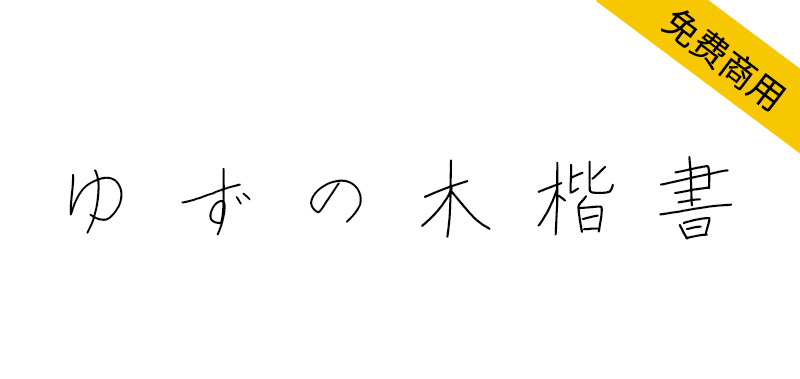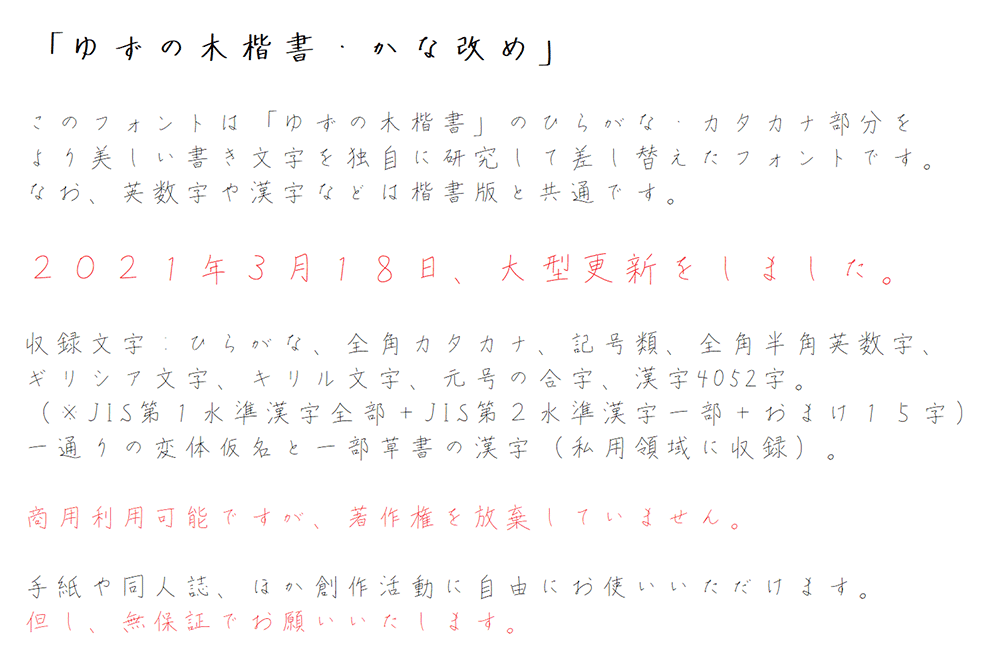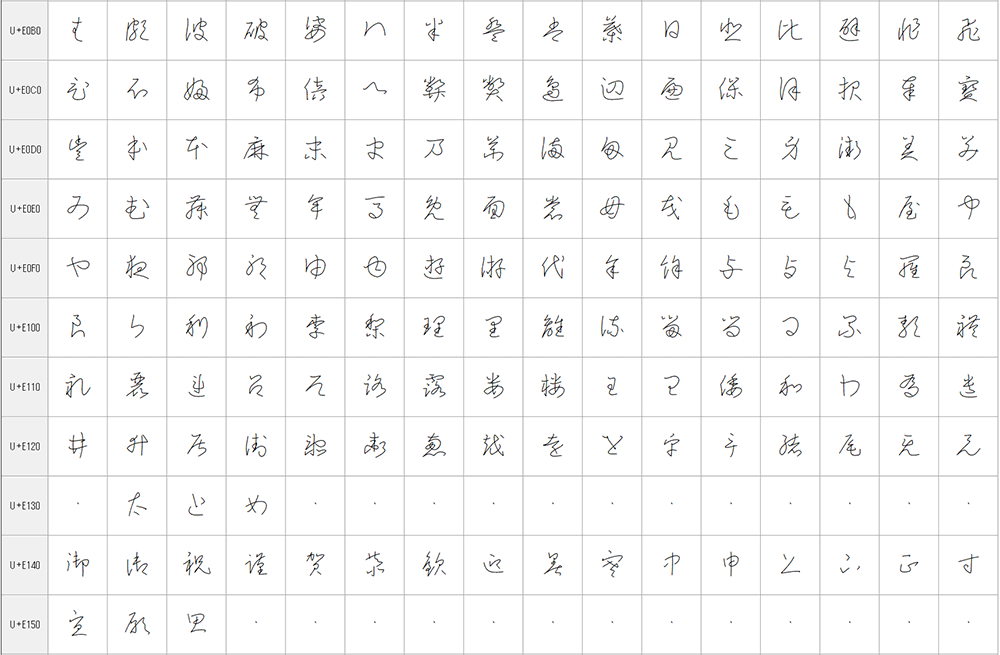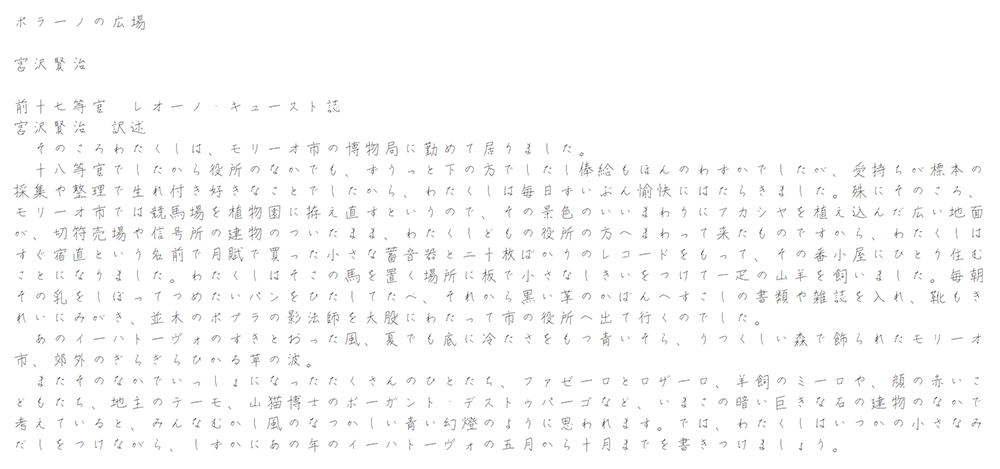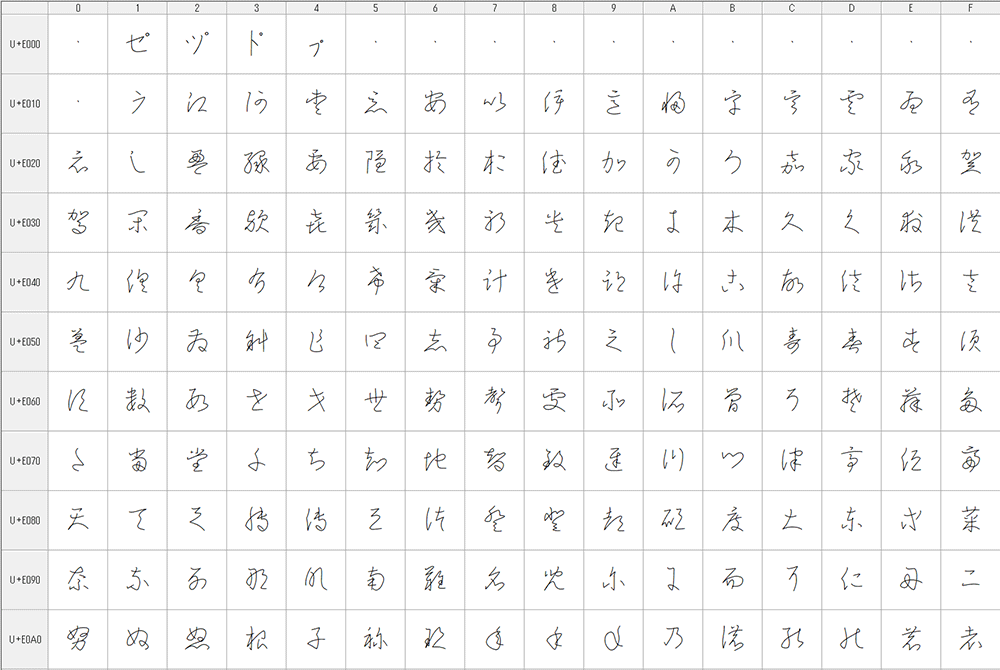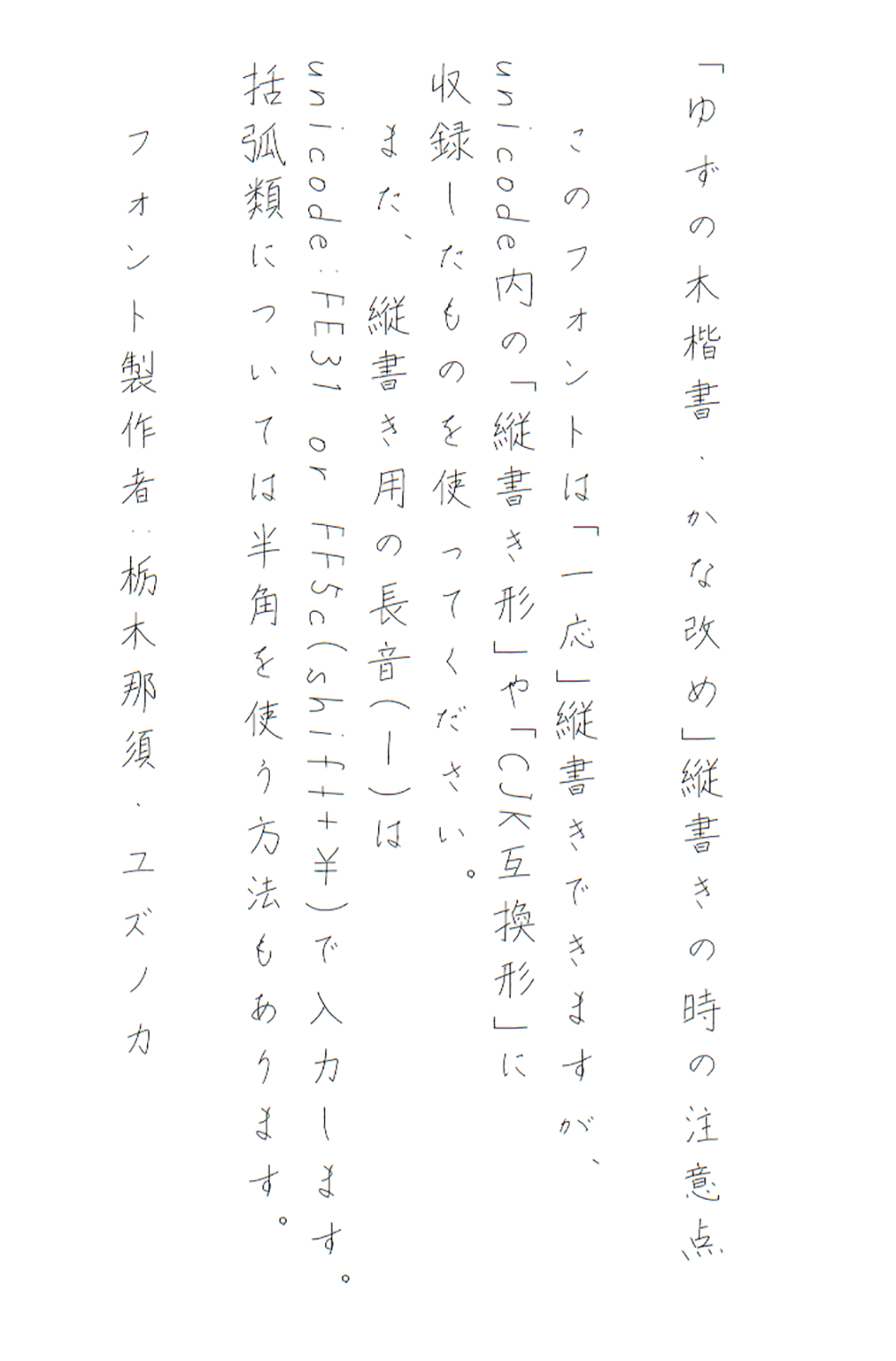
ゆずの木楷書・かな改め是在我个人日常手写字体「柚木楷书」的基础上,对其中的平假名与片假名部分进行了独立研究优化,使其呈现更优美的假名字形,汉字部分则与原版「柚木楷书」保持一致。
收录字符范围:平假名、全角片假名、全角/半角英文数字、基础符号、西里尔字母、希腊字母、日本年号合字、4070个汉字(JIS第一级汉字全部 + JIS第二级汉字部分 + 17个附加字)、全套变体假名及部分草书汉字(收录于私人使用区)
附加内容:在私人使用区额外添加了全套变体假名和部分草书汉字,可书写「御祝」「寸志」「迎春」「お見舞い申し上げます」等传统用语。
このフォントは私自身の普段の手書き文字をフォント化した、「ゆずの木楷書」のひらがな・カタカナ部分を、より美しい仮名文字になるよう独自研究して、差し替えたバージョンで、漢字は「ゆずの木楷書」と共通です。
収録文字:ひらがな、全角カタカナ、全角半角英数字、最低限の記号、キリル文字、ギリシア文字、元号の合字、漢字4070字、(JIS第1水準漢字全部+JIS第2水準漢字一部+おまけ17字)、ひと通りの変体仮名と一部草書の漢字(私用領域に収録)
おまけで私用領域に一通りの変体仮名と一部草書を追加しました。「御祝」「寸志」「迎春」「お見舞い申し上げます」などが書けます。